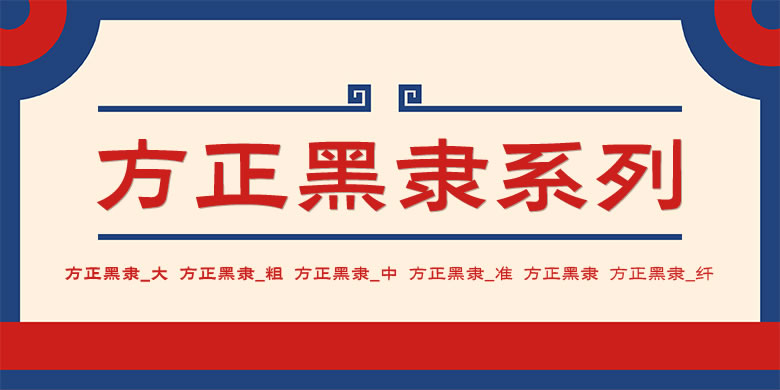
方正黑隶简体
方正黑隶简体是一款非常漂亮的艺术字体,方正黑隶简体广泛用于各种书刊、画册、包装、字体设计的设计中,方正黑隶简体是TrueType字体,方正黑隶简体也是报纸和杂志和书籍中常用的字体, 设计师常用字体,主要用于海报、个性促进品牌标志设计、字体设计、等环境。
在正文排版字体中,隶书的种类相对较少,而风格现代的隶书更是不多。方正黑隶在间架上融合了隶书的传统和现代黑体的笔形特征,把“蚕头雁尾”做成斜笔方头,曲直互用。风格劲爽简约,散发出一种新古典气息,适用于传统文化类的视觉设计。方正黑隶家族包含6款字重,有很好的排版统一性,可直接用于标题和正文的排版。